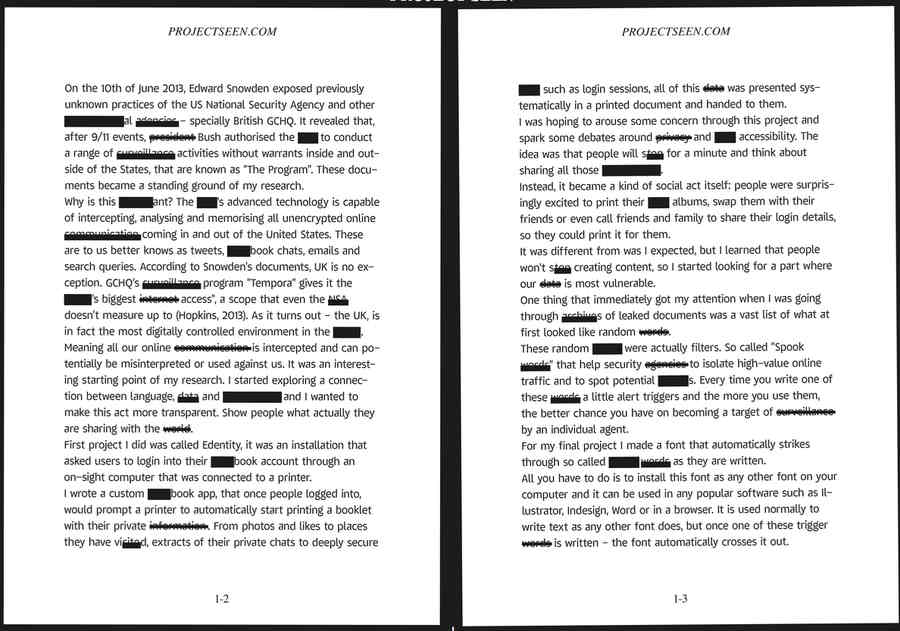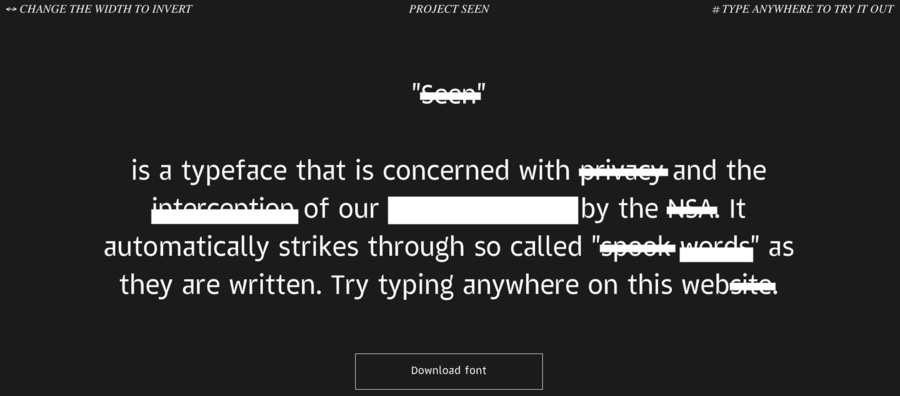
Proyecto “Seen”, es una tipografía gratuita, que se preocupa por la privacidad y la intersección de nuestros mensajes por la NSA (Agencia Nacional de Seguridad de Estados Unidos). La tipografía censura automática mente palabras “sensibles” en idioma ingles como por ejemplo las siguientes; password, NASA, Visa, interception, entre muchas otras más.
Tipografía gratuita que se preocupa por la privacidad en internet
Proyecto Seen surge como un proyecto final para una materia de una Universidad de arte en Londres llamada Central Saint Martins. El que la diseñó se llama Emil Kozole, y la puso en internet para que cualquier persona haga uso de ella, descargándola de manera gratuita.
Lo que hace la tipografía es que cuando escribes ciertas palabras se censuran automáticamente, como si estuvieran subrayadas con un plumón negro de varios grosores. Con el objetivo de complicar la lectura o de plano censurar la palabra completamente.